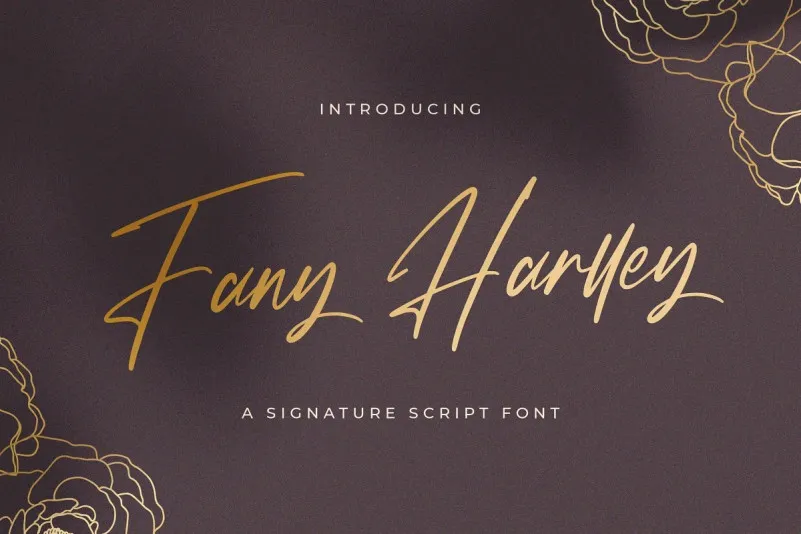
Fany Harlley Font – Download Grátis
A Fany Harley Font é uma escolha perfeita para aqueles que buscam uma mistura elegante de sutileza e entusiasmo na sua próxima criação visual. Com um traço rústico e limpo, inspirado no estilo de uma tinta para caneta felt-tip, esta fonte apresenta caracteres com um charme singular e uma proporção perfeita, criando designs que se adaptam a diversas aplicações. Com seu design sofisticado e harmonizado, esta fonte é ideal tanto para projetos artísticos quanto para trabalhos de design digital. É especialmente adequada para criações que exigem um toque delicado e atencioso à composição, mas também para ideias mais audaciosas que se beneficiam do seu charme elegante. Adicione a Fany Harley Font aos seus projetos mais criativos e veja como ela ilumina suas ideias. Esta fonte é uma ótima escolha para designers que valorizam um equilíbrio entre beleza e simplicidade, proporcionando os elementos necessários para tornar qualquer conceito em algo realmente especial.